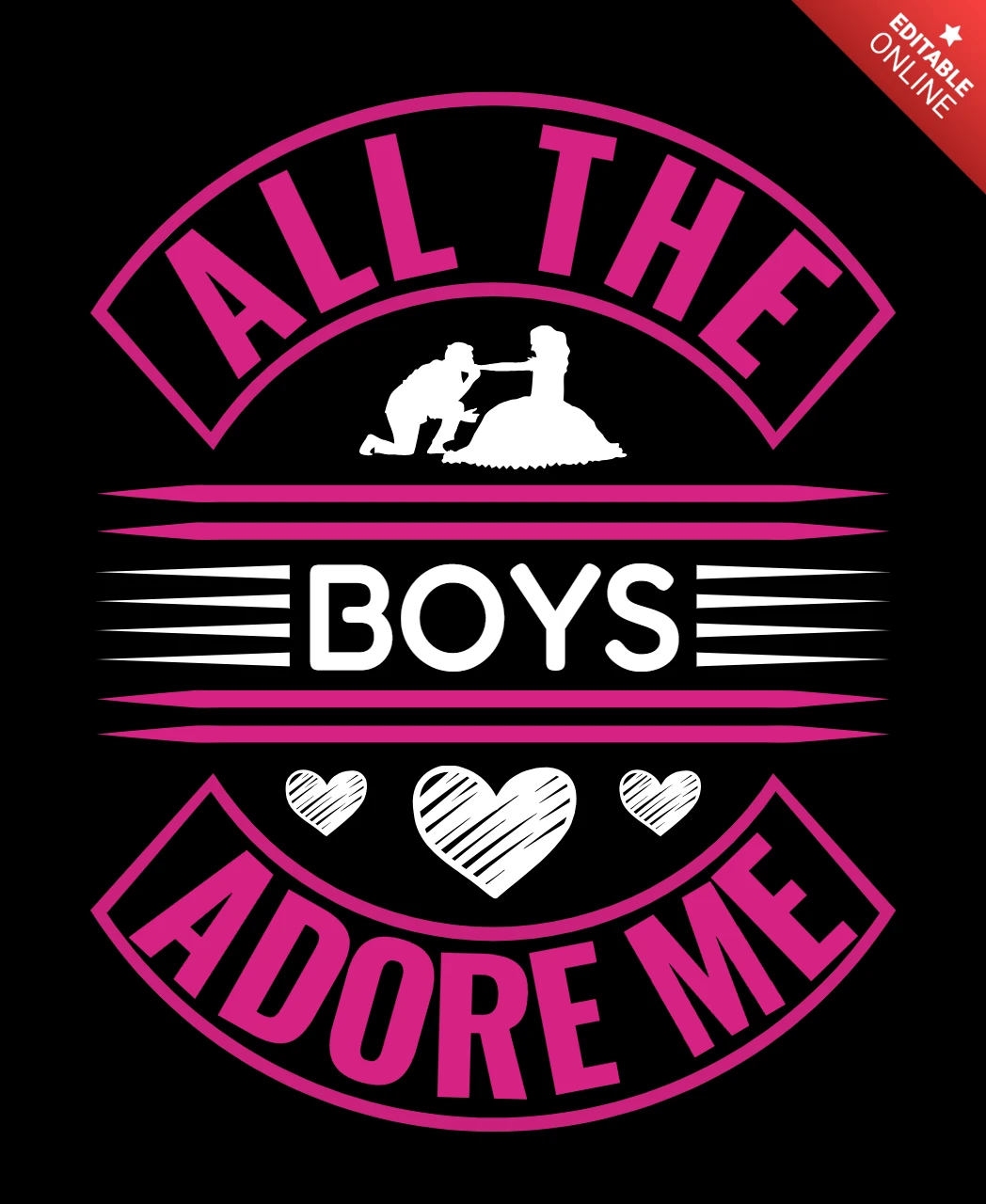
Modèle de typographie vintage ludique pour "all the boys adore me" (tous les garçons m'adorent)
Éditer dans Design Studio Télécharger en JPGLibérez votre créativité grâce à notre modèle de conception ludique, doté d'une typographie audacieuse et d'une ambiance rétro. Il est parfait pour les vêtements et les autocollants qui disent "tous les garçons m'adorent !